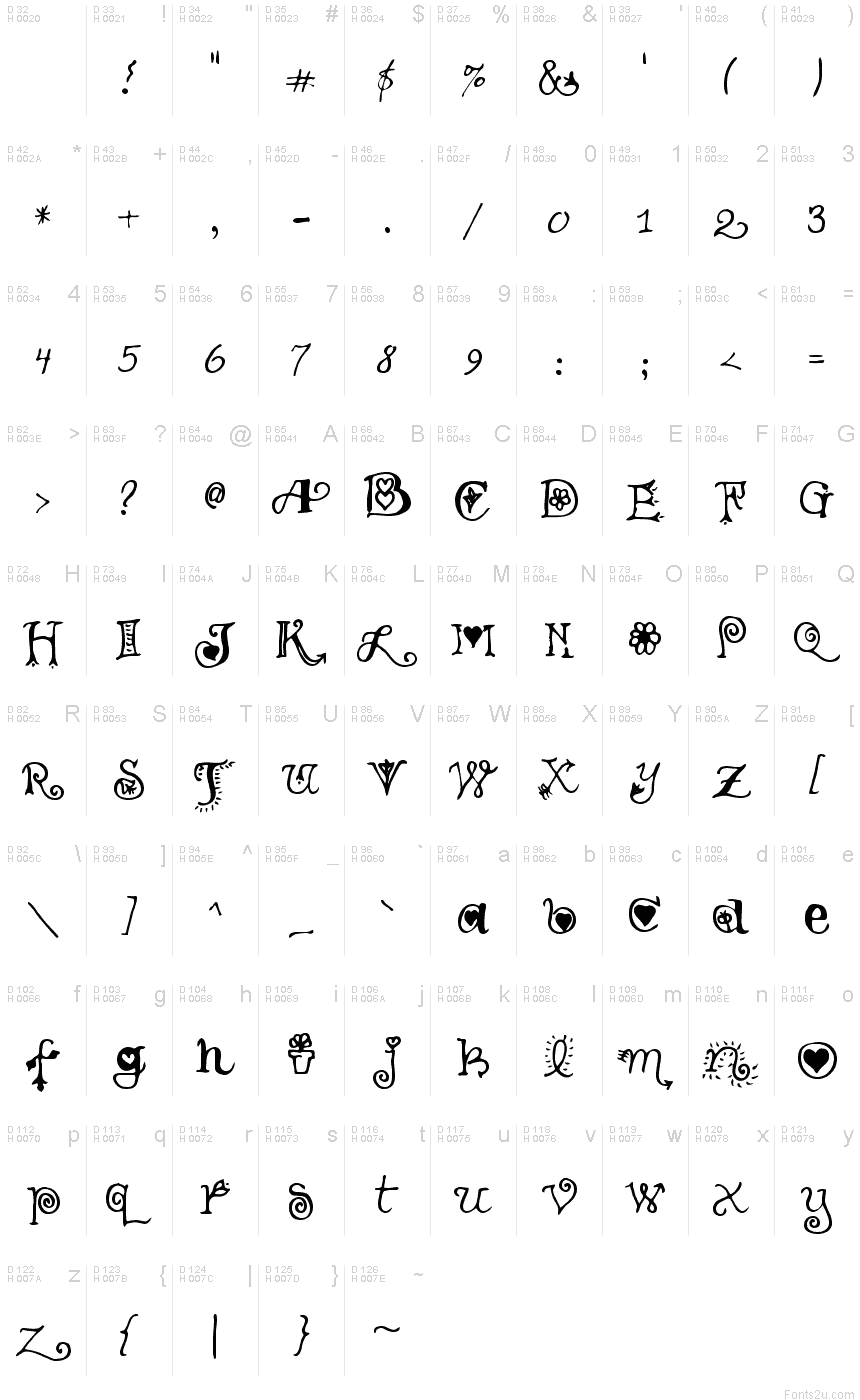
Teenage Girl 3 è un font gratuito in stile doodle, con lo spirito giocoso di un diario adolescenziale. Le lettere mescolano forme cicciotte e arrotondate con piccoli dettagli simili a foglie e germogli: il risultato è che anche i caratteri più semplici sembrano scarabocchiati, decorati e un po' sognanti.
È perfetta per titoli di album di ricordi, packaging per boutique, brand ispirati ai diari, inviti a feste e poster dove serve un tocco informale e fatto a mano. Usala per brevi titoli, copertine o iniziali quando vuoi che i dettagli curvi e le forme a petalo aggiungano un carattere che una font standard non può dare.
Teenage Girl 3